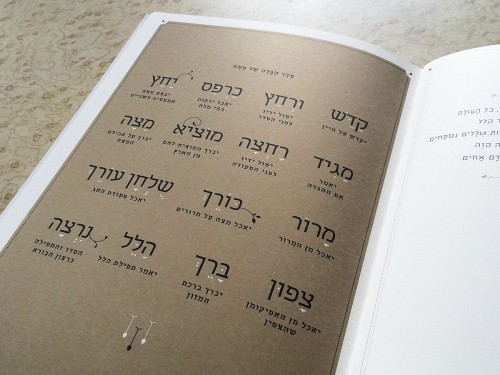
על אודות פונט אסימון
פונט אסימון נוצר מתוך אוסף מגוון של השראות – אותיות נוסטלגיות וקלאסיות מצד אחד ופונטים חדשים ולטיניים מצד שני. חלק נכבד מההשראה לצורות שלד האות לקוח משורשי האות של פונט פרנק־ריהל. לאסימון יש סטייל עדין וגבוה, עכשווי עם רוח נוסטלגית. מצויין לטקסט רץ ולכותרות, לדפוס ולדיגיטל. מומלץ להשתמש בו לתדמיות, לוגואים, שלטי חוצות, טקסט רץ, אריזות ובספרי שירה. ב־2018 בנינו את הפונט מחדש והוספנו לו משקל בינוני וסטנסיל. משקל הסטנסיל לא חושב כמו ״סטנסיל״ רגיל. חלקי האות של המשקל ה״שחור״ הופרדו בחיתוכים אקספרסיביים בטכניקה סיבובית שהתלבשו על הדי־אן־איי של אסימון בצורה אורגנית וייחודית.
המלצת המערכת
השתמשו בו לכותרות או לטקסט־רץ.
עובד נהדר עם הפונטים:
עובד עם הפונטים הלטיניים
Source Sans Pro, Open Sans & Raleway
המלצת שימוש לפי משקל
לייט לכותרות בגודל 24 pt ומעלה
רגיל, בינוני ובולד לטקסט־רץ קריא וזורם וגם לכותרות אלגנטיות
שחור לכותרות בגודל 24 pt ומעלה
סטנסיל לכותרות בגודל 30 pt ומעלה -